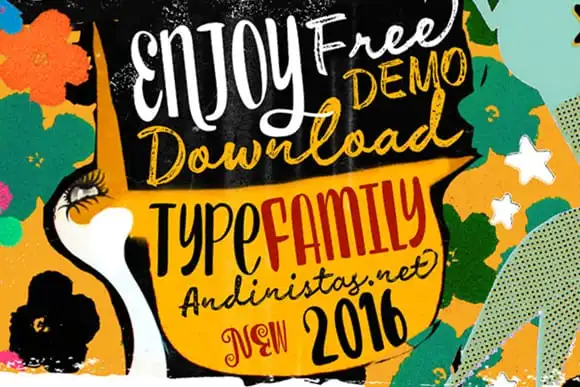
Enjoy Font Family – Download Grátis
Aproveite a experiência única da Enjoy Font Family, uma família de fontes criada pelo designer Andinistas. Essa familia de 5 fontes está concebida para se complementar entre si ou serem usadas de maneira independente. Quando utilizadas como complemento para ilustrações ou projetos mais espontâneos que requerem fontes orgânicas, a família Enjoy é uma ótima escolha. Nela você encontrará atributos expressivos refletidos tanto na escrita em maiúsculas quanto minúsculas e números, todos criados com traços de pincel e esferografia. A estratégia da família é cuidadosamente elaborada para proporcionar um realismo artesanal nas conexões e alternativas para criar letras eloquentes ao início, no meio ou final do palavras sem perder a ordem e a legibilidade. É uma escolha perfeita para quem busca uma fonte que traga vida à sua tipografia de projetos criativos e espontâneos.